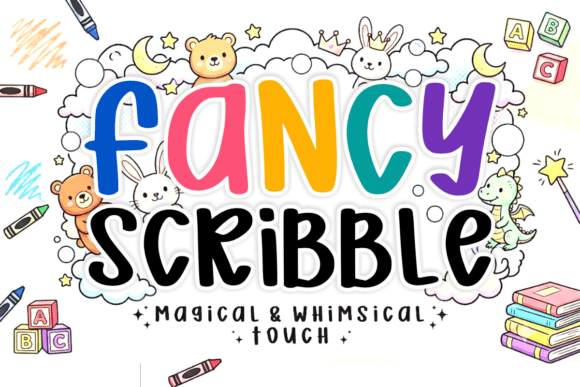
Fancy Scribble
Jika anda sedang mencari aset berkualiti tinggi seperti Fancy Scribble, pakej premium ini merupakan pilihan yang hebat untuk projek kreatif anda.
Dicipta dengan ketepatan, Fancy Scribble menyediakan vektor yang bersih, tipografi yang licin dan lesen komersial untuk ketenangan fikiran.
Sama ada anda mencipta produk POD (Print on Demand), jemputan perkahwinan atau grafik media sosial, Fancy Scribble amat bersesuaian.